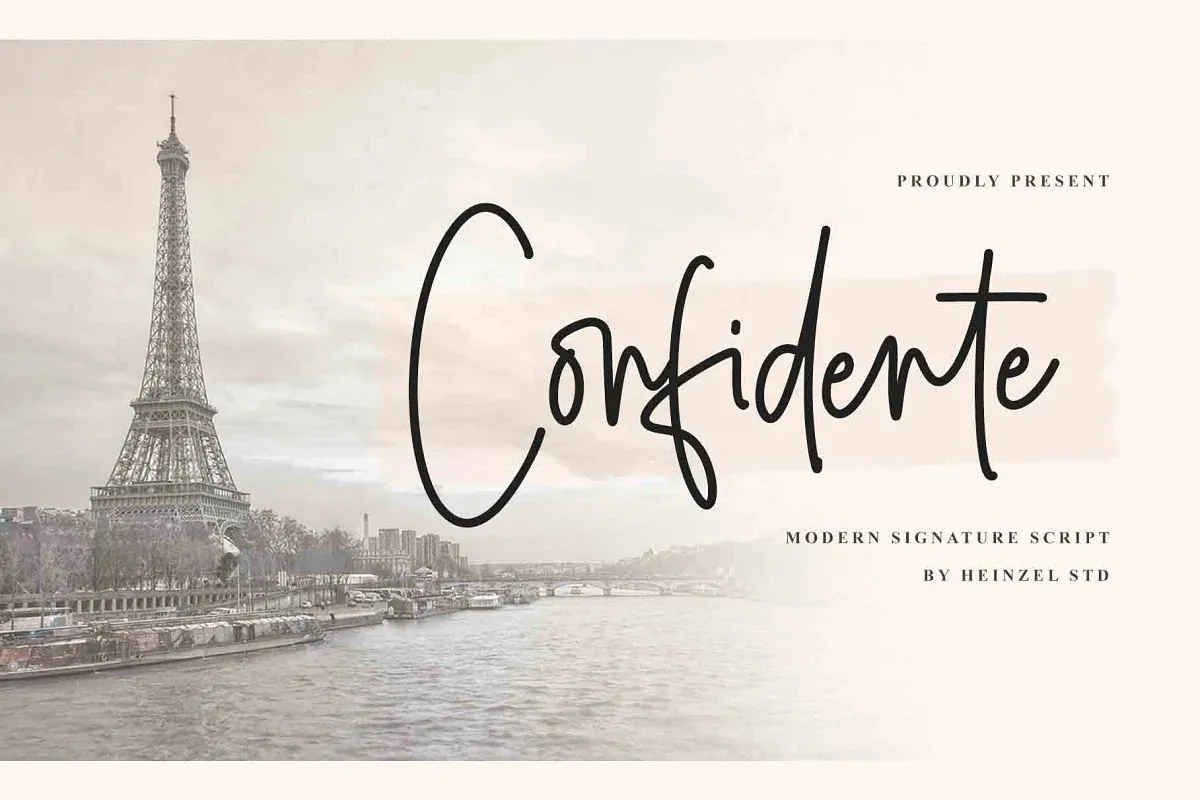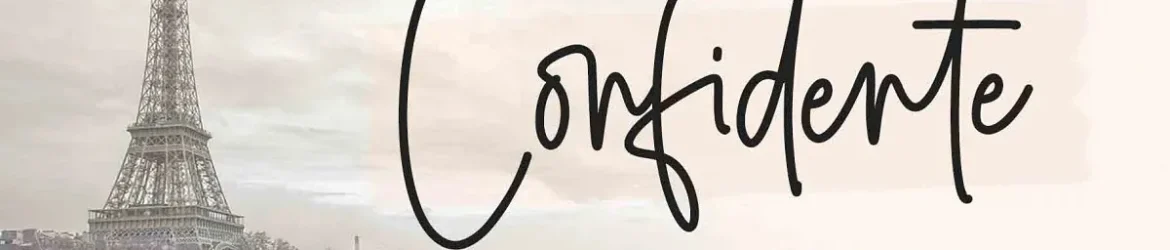
A Confidente Font é uma elegante e fluida fonte escrita a mão que captura os movimentos sutis do texto humano. Suas letras têm um ar leve e gracioso, quase dançando ao longo das linhas de base. Este design inovador não apenas enriquece o conteúdo gráfico em seus projetos mais criativos, mas também as faz destacar-se na cena. O PUA encoding é outro atributo que torna a Confidente Font ainda mais acessível e versátil. Com ele, você pode explorar todos os traços e ligaturas com facilidade, transformando o design de um nível para outro. Seja você uma designer ou um criador de conteúdo, essa fonte está aqui para ajudar a destacar seus conceitos inovadores.